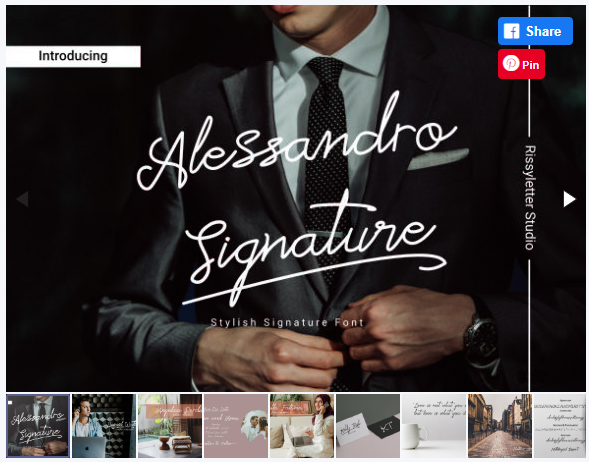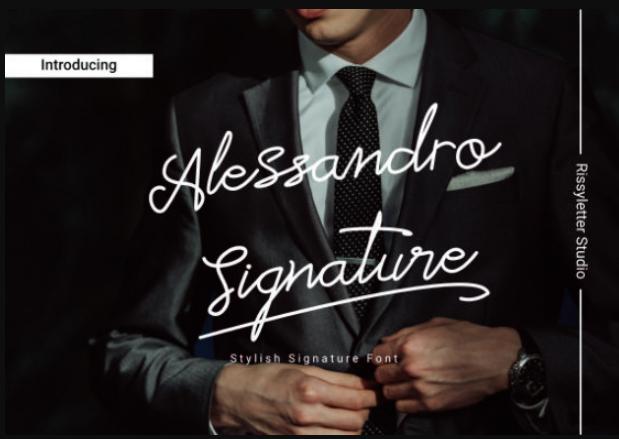
[Creativefabrica] Alessandro Signature Font (Rissyletter Studio)
Alessandro Signature - тонкий и элегантный рукописный шрифт. Его четкие и округлые буквы делают этот шрифт шедевром. Влюбитесь в его невероятно универсальный стиль и используйте его для создания впечатляющих дизайнов!